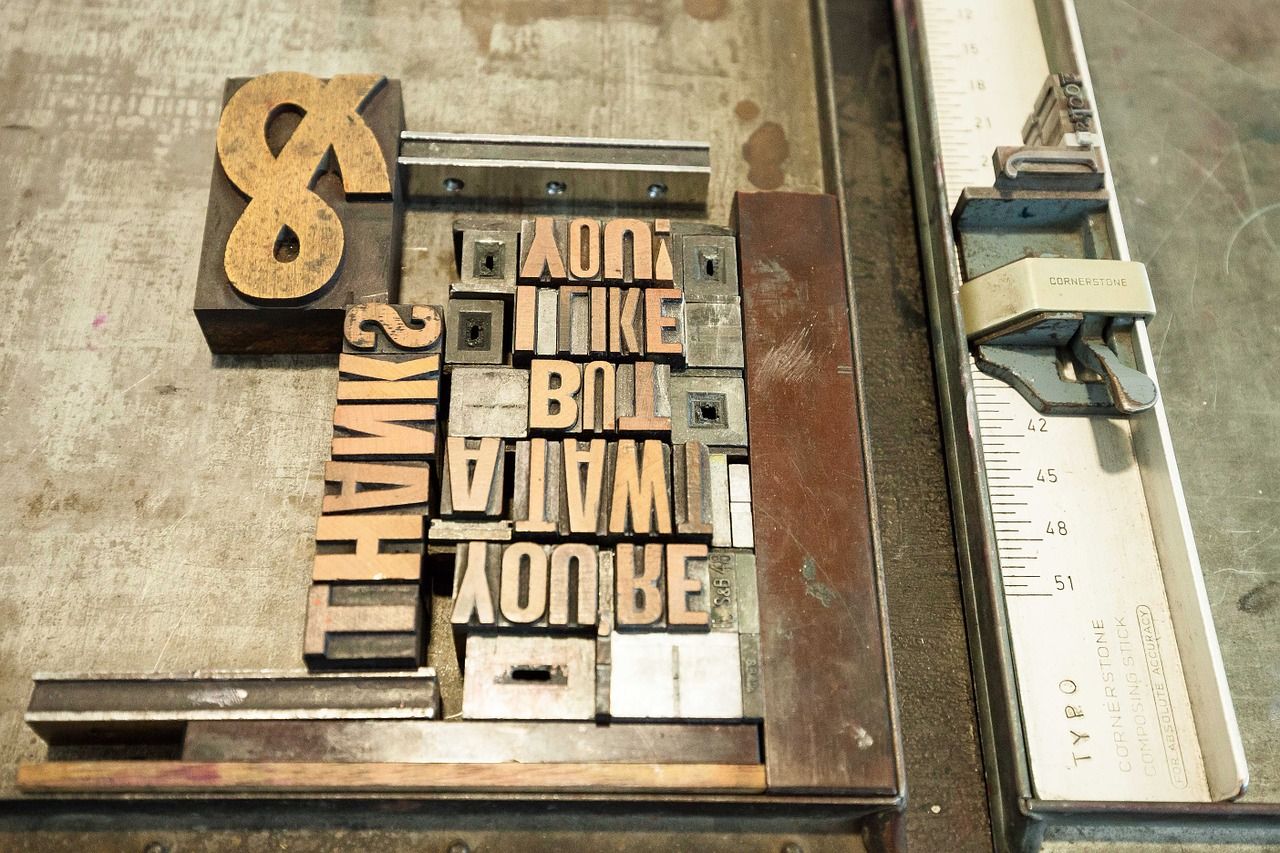
Bei der Erstellung von formellen Texten wie akademischen Arbeiten, Bewerbungsschreiben oder journalistischen Berichten zählt meist nicht nur der Inhalt, sondern auch die Form. Bewusst oder unterbewusst erwarten wir als Leser eines seriösen Textes gewisse typografische Eigenschaften, die Rückschlüsse auf die Quelle und die Textintention zulassen. Die Gestaltung eines Textes wirkt sich direkt auf die Rezeptionssituation aus und sollte deshalb nie vernachlässigt werden. Welche Punkte besonders wichtig für hochwertige Typografie in akademischen und kommerziellen Texten sind, zeigt eine kurze Checkliste der grundlegendsten Merkmale.
1. Unterschiedliche Adressaten brauchen unterschiedliche Typografie
Die Typografie kann als Beeinflussung der Rezeptionssituation zwischen Leser und Text verstanden werden. Autoren und Grafikdesigner sollten sich zunächst bewusst machen, welches Ziel der zu bearbeitende Text verfolgt – ein Text, der Aufmerksamkeit generieren soll, stellt andere Anforderungen an die Typografie, als ein rein informeller Text oder Bericht. Nicht nur bei der Erstellung, auch bei der Gestaltung von Texten steht die Frage im Mittelpunkt: Wie nimmt der Adressat den Text wahr? Je klarer das Ziel des Textes im Voraus formuliert wird, desto leichter wird also die Entscheidung für ein bestimmtes Layout fallen. Für bestimmte Textformen gelten klare No-gos, die Herausgeber vor der Publikation oder Abgabe eines Textes unbedingt recherchieren sollten. Kleiner Tipp: Orientieren Sie sich vor der Layout-Gestaltung Ihres Textes an vergleichbaren Artikeln und Produkten, um ein Gefühl dafür zu entwickeln, wie Ihr Text herausstechen könnte. Sowohl auf der Makro- als auch auf der Mikro-Ebene herrschen in jedem typografischen Arbeitsbereich bestimmte Trends und Normen vor, die unterschiedlich viel Spielraum in der Gestaltung lassen.
2. Neue Medien, neue Mittel
Neben der Textbotschaft und dem Adressaten ist für eine professionelle Typografie vorallem das Medium bestimmend. Für gedruckte Texte gelten andere typografische Regeln als für Texte, die auf digitalen Medien gelesen werden. Die meisten Online-Artikel werden deshalb in unterschiedlichen Ausführungen designt. Auf dem Smartphone lassen sich kurze Textabschnitte mit vielen Silbentrennungen am besten lesen, während dunkle Hintergrundfarben und helle Schrift für Leser an Computer- und TV-Bildschirmen am angenehmsten wirken. Ähnliche Unterschiede bestehen bei gedruckten Büchern und E-Books. Bei Druckartikeln kann das Layout außerdem maßgebend für die Herstellungspreise sein. Jedes neue Medium verlangt also auch nach einem neuen Layout. Durch manuelle Testläufe vor der Veröffentlichung stellen Sie sicher, dass Ihr Text auf jedem Medium lesbar ist und ansprechend wirkt. Das Layout älterer Artikel sollten Sie regelmäßig an bestehende Templates und die gängige Technik anpassen, um eine einheitliche Optik zu schaffen.
3. Aufmerksamkeit generieren und Inhalt vermitteln
Ein Ziel haben alle publizierten Texte gemeinsam: Sie sollen gelesen werden. In unserer digitalisierten und schnelllebigen Gesellschaft wird es deshalb immer wichtiger, die Botschaft eines Textes unkompliziert zu vermitteln. Aussagekräftige Überschriften, abgesetzte Zusammenfassungen und ein gut lesbares Schriftbild sind die Grundvoraussetzungen für leicht verständliche Texte. Kleine Veränderungen an der Schriftgröße, der Absatzstruktur und dem Satz können die Lesbarkeit eines Textes dabei deutlich erleichtern oder erschweren. Journalistische Artikel und Blogeinträge sollten in möglichst kurzen Einheiten gestaltet werden. Grafiken und Bilder lockern das Schriftbild weiter auf. In akademischen Texten und literarischen Narrationen wirken diese Elemente eher ablenkend. Hier kommt es darauf an, sinnvolle Leseeinheiten zu schaffen, die das Tempo beim Lesen vorgeben.
4. Die Typografie bestimmt das Image
Die Gestaltung einer Homepage oder eines Druckprodukts ist entscheidend für das Image des Herausgebers. Über das Layout kann ein Autor oder ein Unternehmen eine Vielzahl von Eindrücken vermitteln. Wiederkehrende Farben und Grafiken unterstützen die Markenbildung und lassen den Leser auf den ersten Blick erahnen, um welche Art von Text es sich handelt und worauf er sich thematisch einzustellen hat. Plagiatisten und Trittbrettfahrer machen gern Gebrauch von diesem Effekt und gestalten ihre Artikel identisch zum Layout erfolgreicher Konkurrenten. Sobald Herausgeber einen gewissen Bekanntheitsgrad erreicht haben, sollten sie sich deshalb über Markenschutz und Patentierung informieren.
5. Die eigene Schrift als Erkennungsmerkmal
Ein eigenes Schriftbild ist das stärkste Wiedererkennungsmerkmal für Herausgeber und Autoren. Wenn Sie regelmäßig Artikel verfassen und Druckprodukte herausgeben, ist es sinnvoll, eine durchgängige Schriftart zu wählen und diese beizubehalten. Allzu dekorative Schriftarten sollten Sie nur im Titel oder im Untertitel verwenden – für längere Textpassagen sind Standard-Schriftarten wie Times New Roman und Arial die Norm. Durch leichte Variationen in der Breite und dem Abstand der Buchstaben können Autoren auch genormte Texte leicht individualisieren. Beim Erstellen einer eigenen Schriftart sollten Designer auf Schreibschrift-Elemente verzichten und stattdessen eine saubere Druckschrift wählen. In formellen Anschreiben und akademischen Arbeiten vermittelt ein sauberes Schriftbild Professionalität und Sorgfalt, während ein Standard-Blocksatz für werbende Artikel und persönliche Reviews zu streng scheint.
6. Optimieren Sie den Lesefluss
In einem professionell gesetzten Text sollte der Leser keine Auffälligkeiten finden, die auf die Herstellung zurückzuführen sind. Die Abstände zwischen den Wörtern sollten überall etwa gleich groß sein, sodass ein gleichmäßiges Raster entsteht. Bei Texten mit besonders langen Wörtern ist das oft gar nicht so leicht. Durch Silbentrennung können Lücken im Text behoben werden. Zusätzlich zur automatischen Silbentrennung prüfen erfahrene Typographen jeden Textblock genau und passen die Silben gegebenenfalls manuell an, um das Textraster zu optimieren. Allzu viele Silbentrennungen unterbrechen den Lesefluss wiederum – achten Sie darauf, dass maximal zwei aufeinanderfolgende Zeilen mit Silbentrennungen enden. Ein weiteres wichtiges Qualitätsmerkmal ist die Vermeidung von alleinstehenden Zeilen am Seitenanfang oder Seitenende. Die sogenannte Hurenkindregelung kann mit den meisten Textprogrammen automatisch angewendet werden, professionelle Texter sollten aber auch hier manuell prüfen, ob das Absatzverhältnis stimmig erscheint. Bei einem 1,5-fachen Zeilenabstand lassen sich auch klein gedruckte Texte flüssig lesen, ohne dass der Leser mit den Augen zwischen den Zeilen verrutscht.
7. Trends und Inspirationen finden
Fällt Ihnen ein Text positiv ins Auge, können Sie viel aus einer kleinen Strukturanalyse lernen. In jeder Branche herrschen andere Trends und Normen – Abschauen ist also ausdrücklich erlaubt. Designer setzen bei der Erstellung von Layouts meist auf einfache wahrnehmungspsychologische Phänomene – Rot dient zum Beispiel als universelle Warnfarbe, während Pastelltöne und weiche Kontraste das Auge entspannen. Weniger ist mehr! Durch kleine Raffinessen wirkt ein Text meist deutlich ansprechender als durch auffällige Hingucker.